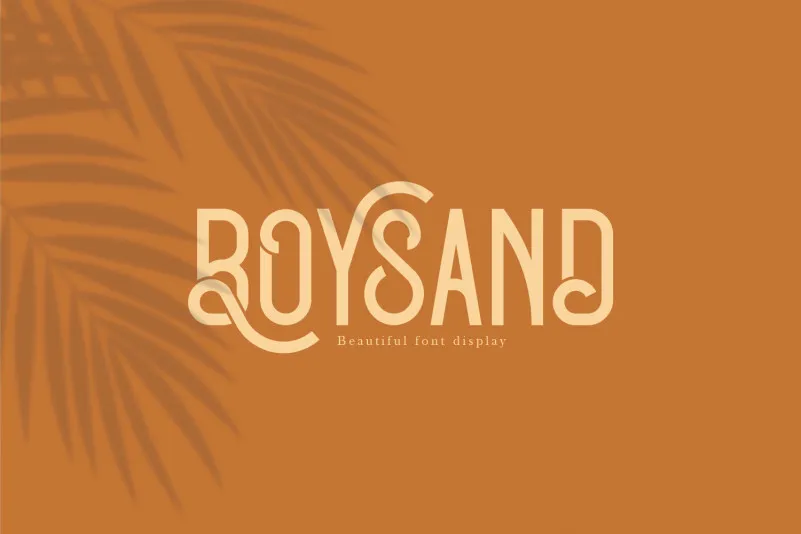
Boysand Display Font
A fonte Boysand Display é uma fonte san serif que transmite um estilo vintage moderno. Ela está completa com letras maiúsculas, minúsculas e ligaduras, o que oferece inúmeras possibilidades de design, tornando-a perfeita para seus trabalhos como cartazes, logotipos, revistas, capas, bandeiras ou até mesmo arte em grande escala. Esta font é ideal tanto para estilos gráficos convencionais quanto para elementos que exigem um toque vintage contemporâneo. Seja você uma marca querendo dar vida às suas peças visuais, um designer de logotipos buscando algo único e atemporal ou um autor independente criando capas para seus livros, a font Boysand Display é sua escolha perfeita.